Font chữ đẹp cũng là một trong những yếu tố quan trọng tạo nên những bản thiết kế ấn tượng. Có bao giờ bạn thấy một font chữ rất đẹp, nhưng khi sử dụng nó thì lại bị lỗi do font đó không hỗ trợ phiên bản tiếng Việt không?
Một font chữ đẹp không chỉ nằm ở nét chữ nghệ thuật thu hút, mà nó là tổng hòa ở các yếu tố kiểu dáng, yếu tố dễ đọc và phù hợp vào từng bối cảnh. Dưới đây là tổng hợp 15 font chữ đẹp dành cho Adobe Premiere mà bạn có thể tham khảo khi edit video:
Arial: là một font chữ sans-serif phổ biến, dễ đọc và thường được mọi người sử dụng khá nhiều trong các tài liệu, thiết kế,...
Futura: cũng là một font chữ sans-serif với kiểu dáng hiện đại, đường nét mạnh mẽ.
Gotham: có thiết kế đơn giản, mạnh mẽ nhưng cũng rất dễ đọc và phù hợp cho nhiều loại thiết kế.
Roboto: đây cũng là một trong những font chữ việt hóa phổ biến, mang đến nét hiện đại, gọn gàng cho thiết kế.
Open Sans: font này mang lại cảm giác mở rộng, thân thiện, dễ đọc dù bất kể kích cỡ nào.
Avenir: có đường nét thanh thoát, mang lại cảm giác cân đối giữa hiện đại và cổ điển, tạo cho người xem video cảm giác dễ chịu khi đọc.
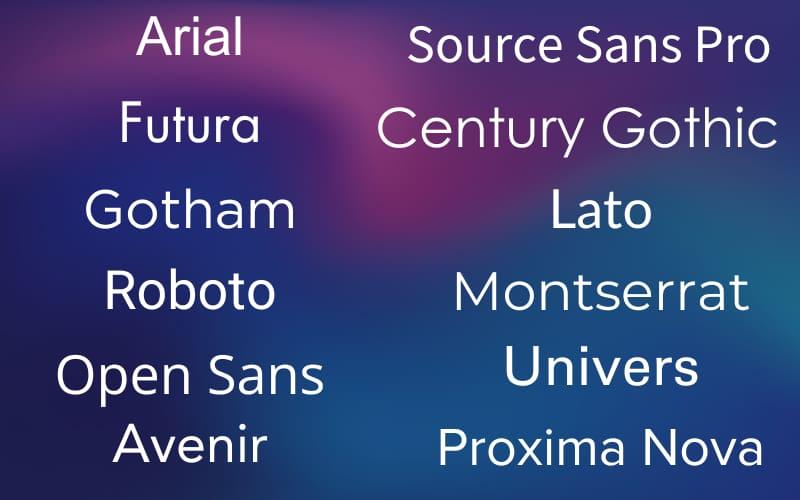
Source Sans Pro: đây là font được thiết kế đặc biệt cho màn hình kỹ thuật số, dễ đọc và không gây mỏi mắt.
Century Gothic: có thiết kế đơn giản, thanh thoát thường dùng trong các văn bản ở bài thuyết trình, tài liệu học thuật, hay thiết kế đồ họa.
Lato: font chữ có các nét bo tròn nhẹ nhàng mang lại cảm giác thân thiện, gần gũi.
Montserrat: một font chữ hiện đại có đường nét rõ ràng phù hợp dùng trong tiêu đề, logo,...
Univers: là một font chữ sans-serif cổ điển được sử dụng linh hoạt trong nhiều chủ đề thiết kế. Đặc biệt, font chữ này cũng có nhiều kiểu độ dày khác nhau để áp dụng cho nhiều trường hợp.
Proxima Nova: là font sans-serif với đường nét mềm mại, tạo nên sự cân bằng hoàn hảo cho văn bản trong thiết kế.